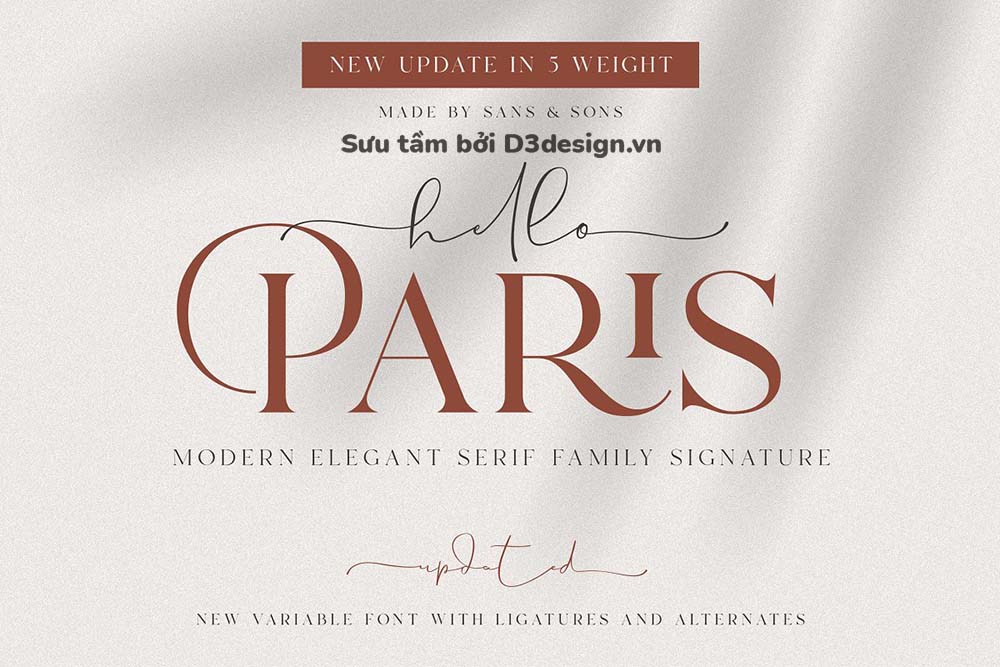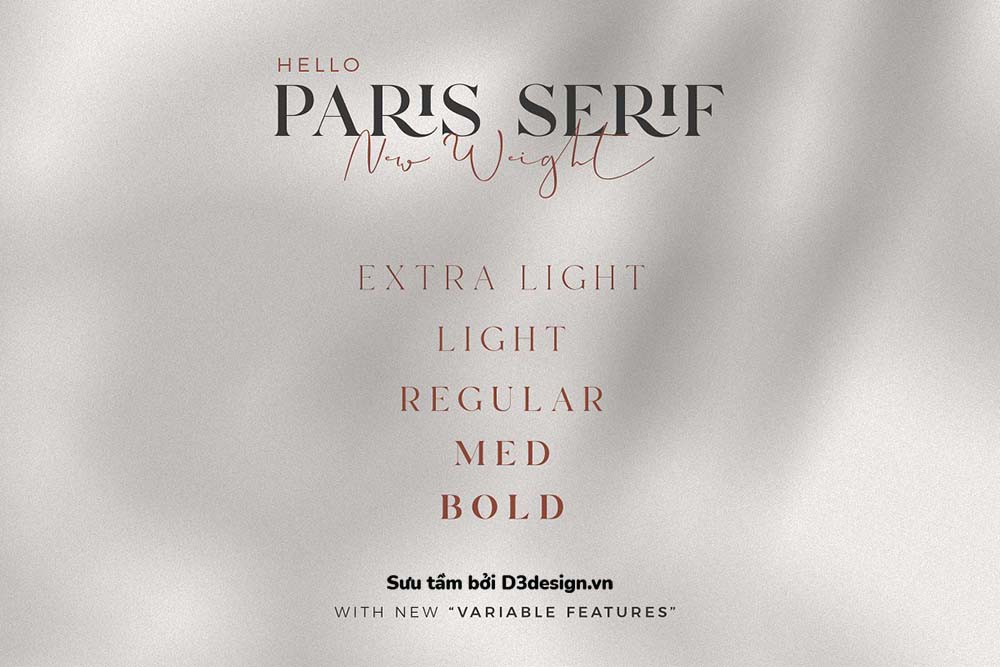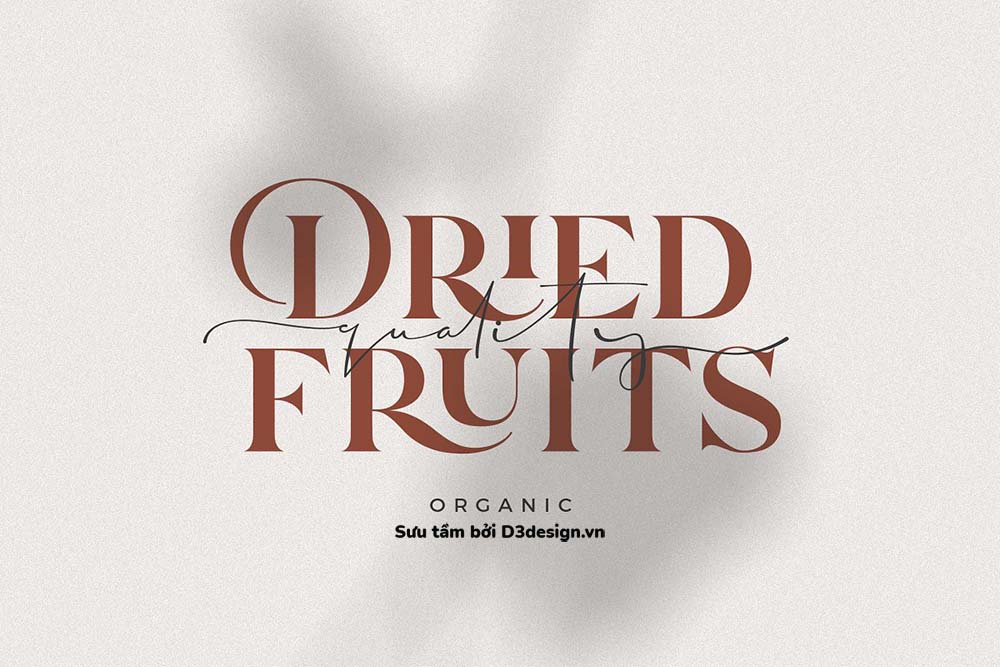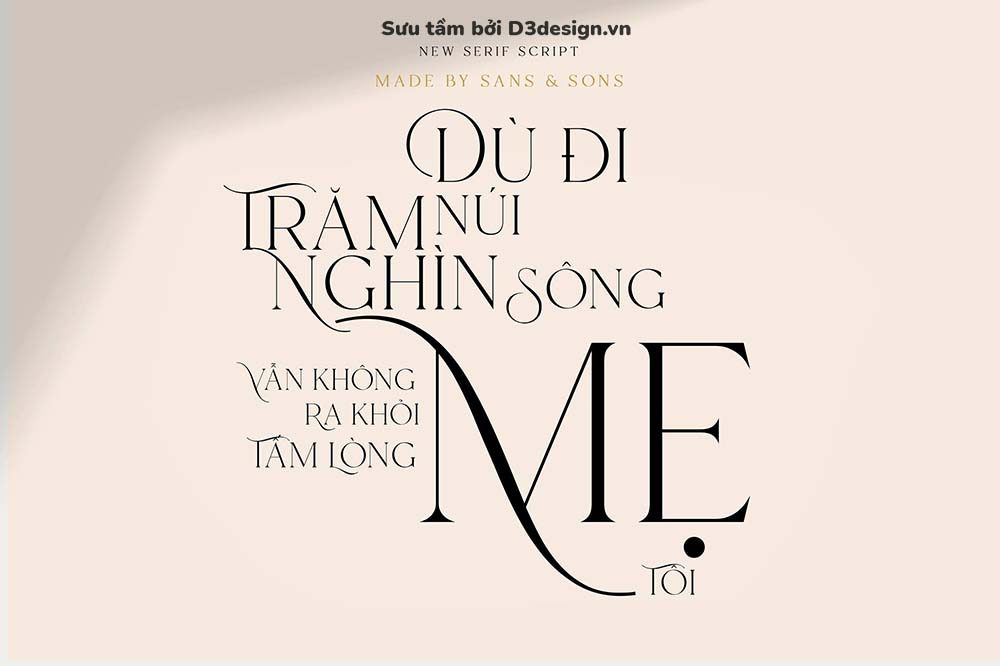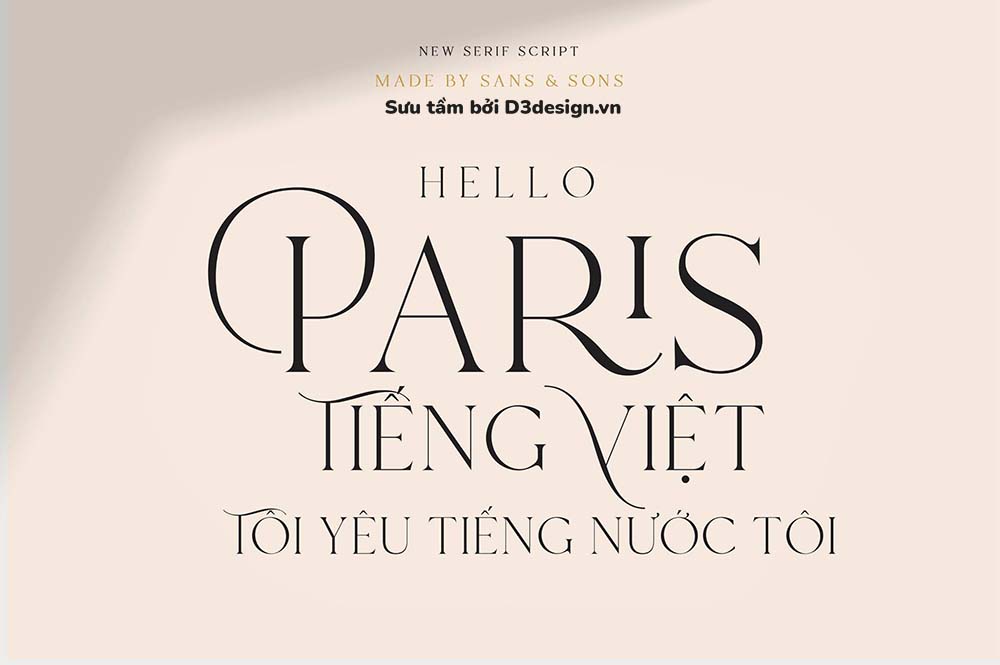
Hello Paris Việt Hoá - Font Chữ Hiện Đại Và Đẹp Mắt
Font Hello Paris có thể nói là một trong những font chữ tuyệt đẹp với phong cách hiện đại, bạn có thể sử dụng nó cho thiết kế thương hiệu, logo, thiệp mời...